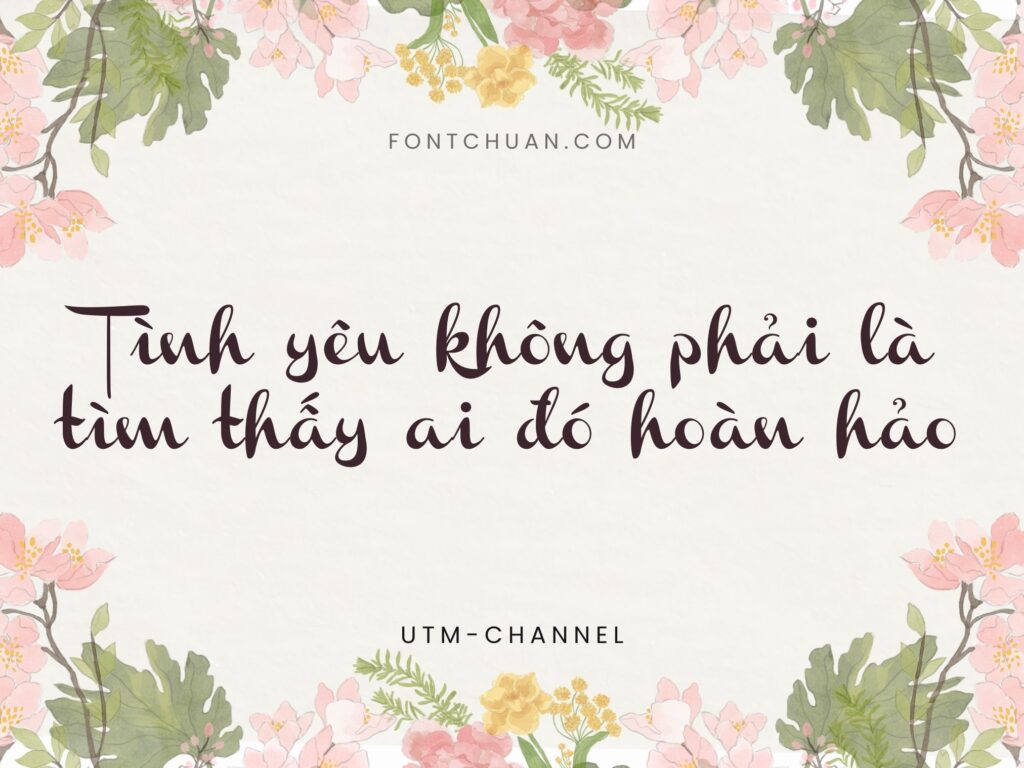
Font UTM Channel Việt Hóa
UTM Channel là một Font Script mang phong cách Font Handwritten thanh lịch, được Việt hóa từ font chữ Channel do Måns Grebäck thiết kế. Kiểu chữ này nổi bật với các ký tự nối liền mạch, đường nét mềm mại và uyển chuyển, tạo cảm giác sang trọng và hiện đại. Phiên bản Việt hóa được thực hiện bởi Unicode Thiên Minh, hỗ trợ đầy đủ tiếng Việt cùng hơn 100 ngôn ngữ khác. Đây là một trong những font được cộng đồng thiết kế sưu tầm và chọn lọc nhằm đáp ứng nhu cầu đa dạng trong thiết kế.
UTM Channel có cấu trúc chữ với các nét thanh mảnh và độ nghiêng nhẹ, tạo nên sự hài hòa và dễ đọc. Font này phù hợp cho các ứng dụng như thiết kế logo, tiêu đề, thiệp mời và các ấn phẩm in ấn yêu cầu sự tinh tế và nghệ thuật. Các ngành nghề như quảng cáo, giáo dục, công nghệ và bất động sản có thể tận dụng UTM Channel để tạo điểm nhấn độc đáo trong thiết kế.